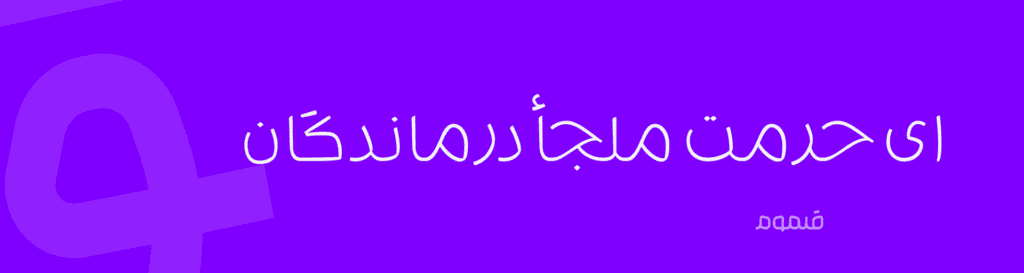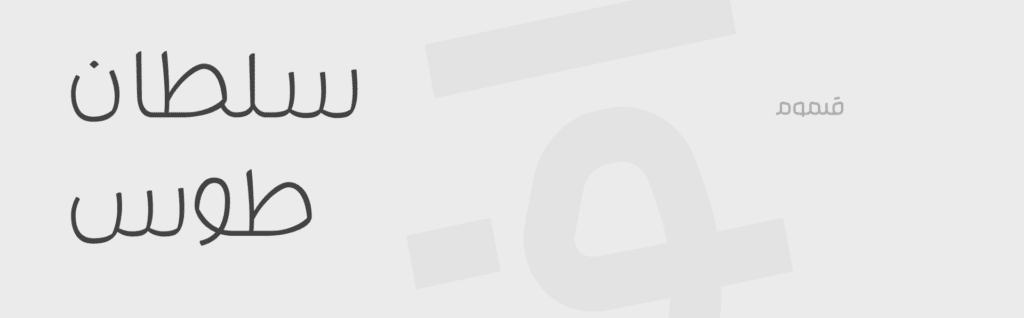
دانلود فونت عربی ملصق
اگه بدنبال فونتی هستی که باهاش عکس نوشته های جذاب طراحی کنی، این فونت بشدت برات مناسبه. فونت ملصق یک فونت عربیه که به صورت ۱۰۰ درصدی از نوشتار فارسی پشتیبانی میکنه. پیشنهاد میکنم این فونت رو در نوشته های کوتاه استفاده کنید.
molsag arabic font
فونت عربی ملصق با دارا بودن حروف هندسی شده، بر زیبایی نوشته های شما اضافه میکنه. کافیه از این فونت در متن‌ها و عناوین استفاده کنین و جذابیتش رو متوجه بشین.
از کاربرد‌های جذاب فونت ملصق، استفاده اون در عکس نوشته هاست. شما میتونین از این فونت برای متن‌های نسبتا بلند هم استفاده کنید. خوانایی فونت ملصق باعث جذابیت طرح شما میشه.